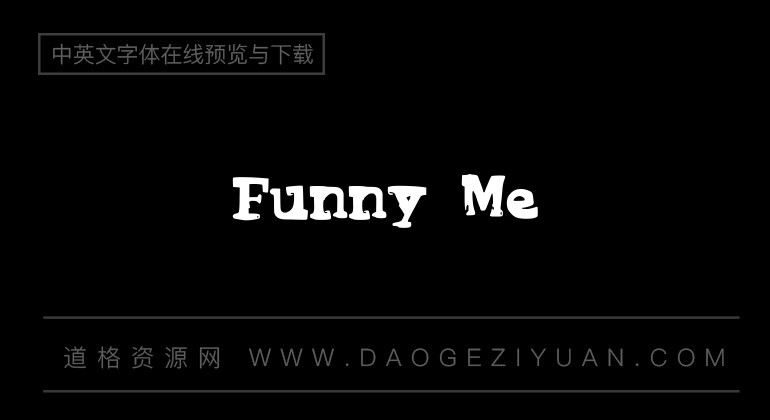
Funny Me
吧 Funny Me 字体是一款由Fontfabric公司设计的手写体字体,它的特点是曲折的线条,让文字看起来更有趣。它的字母和符号都是用粗细不一的笔触描绘出来的,整个字体看起来更加自然,更加活泼。Funny Me 字体可以用于印刷品、海报、广告等,也可以用于网页设计、桌面出版、视频制作等,让你的设计更加有趣。
Funny Me是一款非常不错的手写艺术字体,具有很好的视觉感,适合于文化类的宣传设计、商业类品牌的广告和产品包装设计以及个性化文字排版等较多场景。